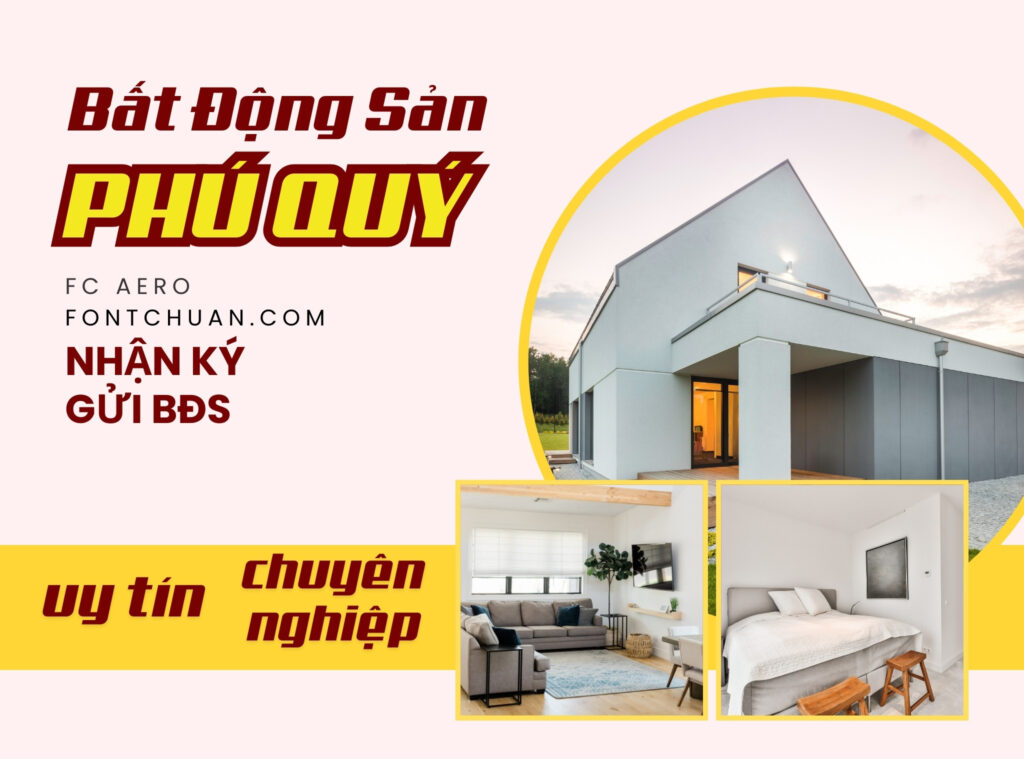
Aero là một họ font sans-serif hiện đại, được thiết kế bởi Labor & Wait và phát hành vào khoảng năm 2024. Với thiết kế tinh tế và đa dạng về trọng lượng, Aero mang lại sự linh hoạt cho các dự án thiết kế. Bên cạnh các ứng dụng chuyên nghiệp, Aero cũng có thể được sử dụng như một Font Lễ hội, tạo điểm nhấn sinh động, vui tươi cho các poster, banner, thiệp mời hoặc các ấn phẩm sự kiện đặc biệt.
Với cấu trúc chữ hình học, độ dày đồng nhất và thiết kế tinh tế, Aero phù hợp cho các thiết kế yêu cầu sự hiện đại và chuyên nghiệp. Đặc biệt, font này thích hợp cho các ngành nghề như bất động sản, quảng cáo, thiết kế bản hiệu, băng rôn, thiết kế thương hiệu và lĩnh vực truyền thông, nơi cần sự kết hợp giữa thẩm mỹ hiện đại và chức năng truyền tải thông điệp.